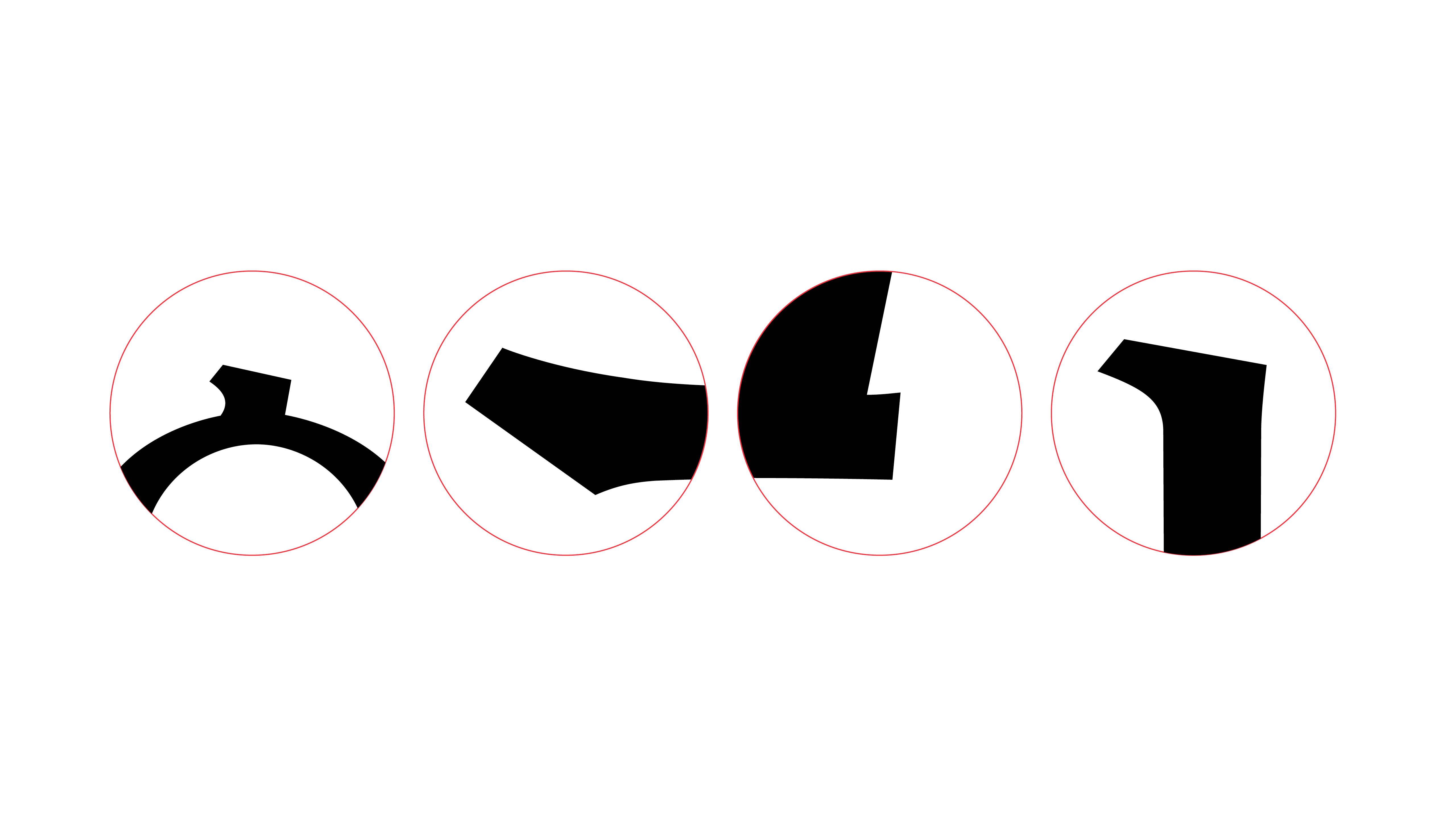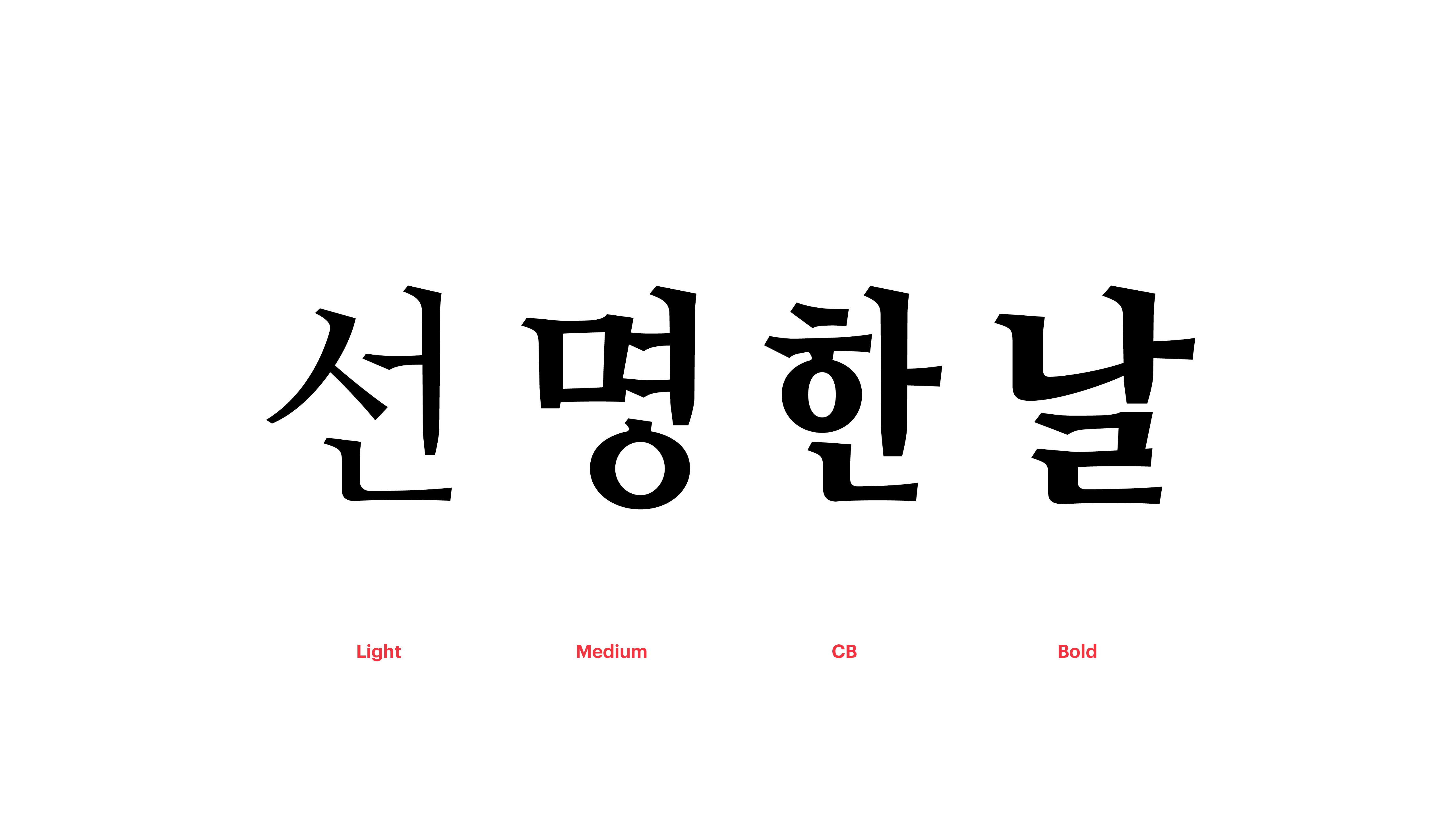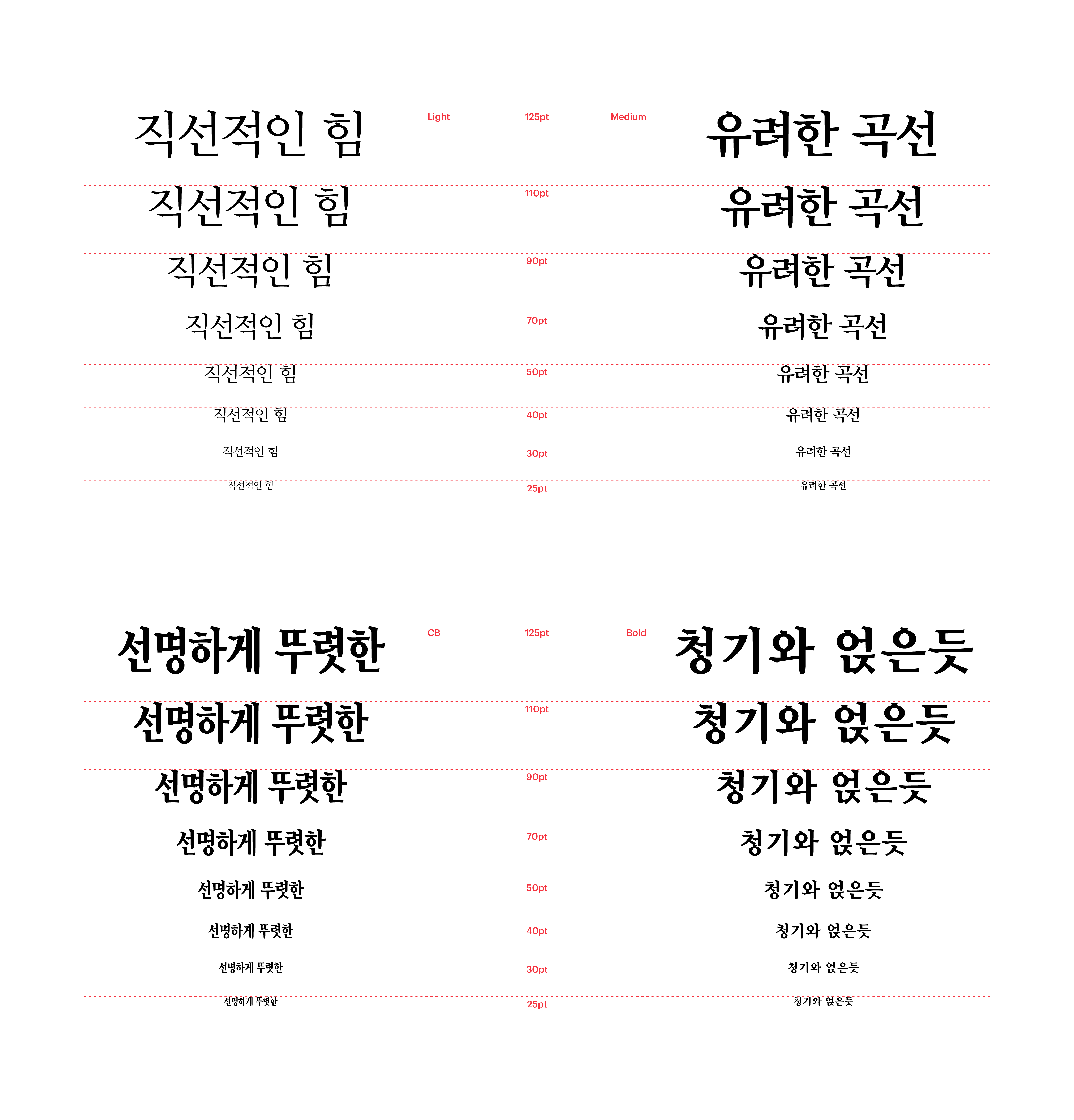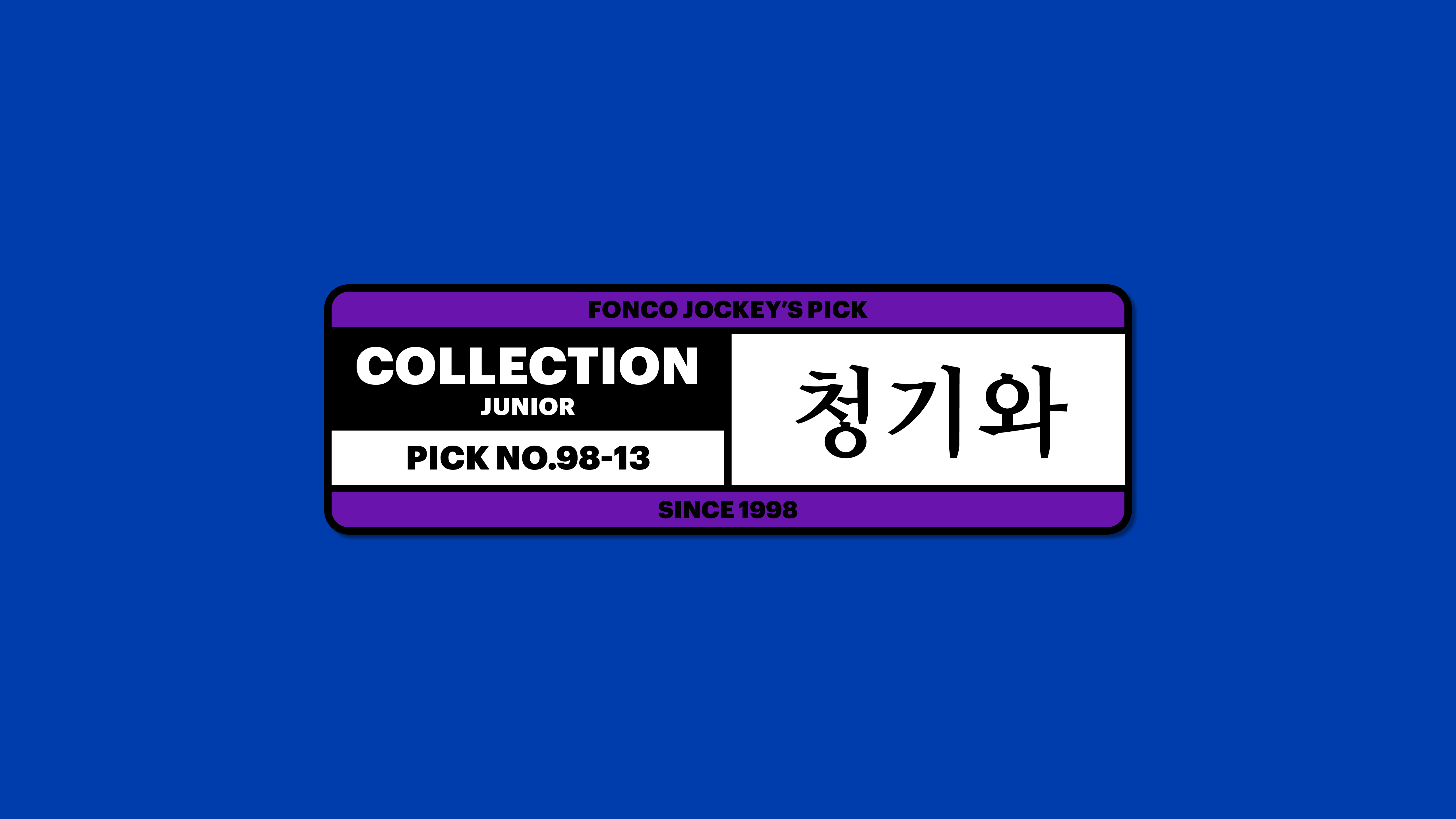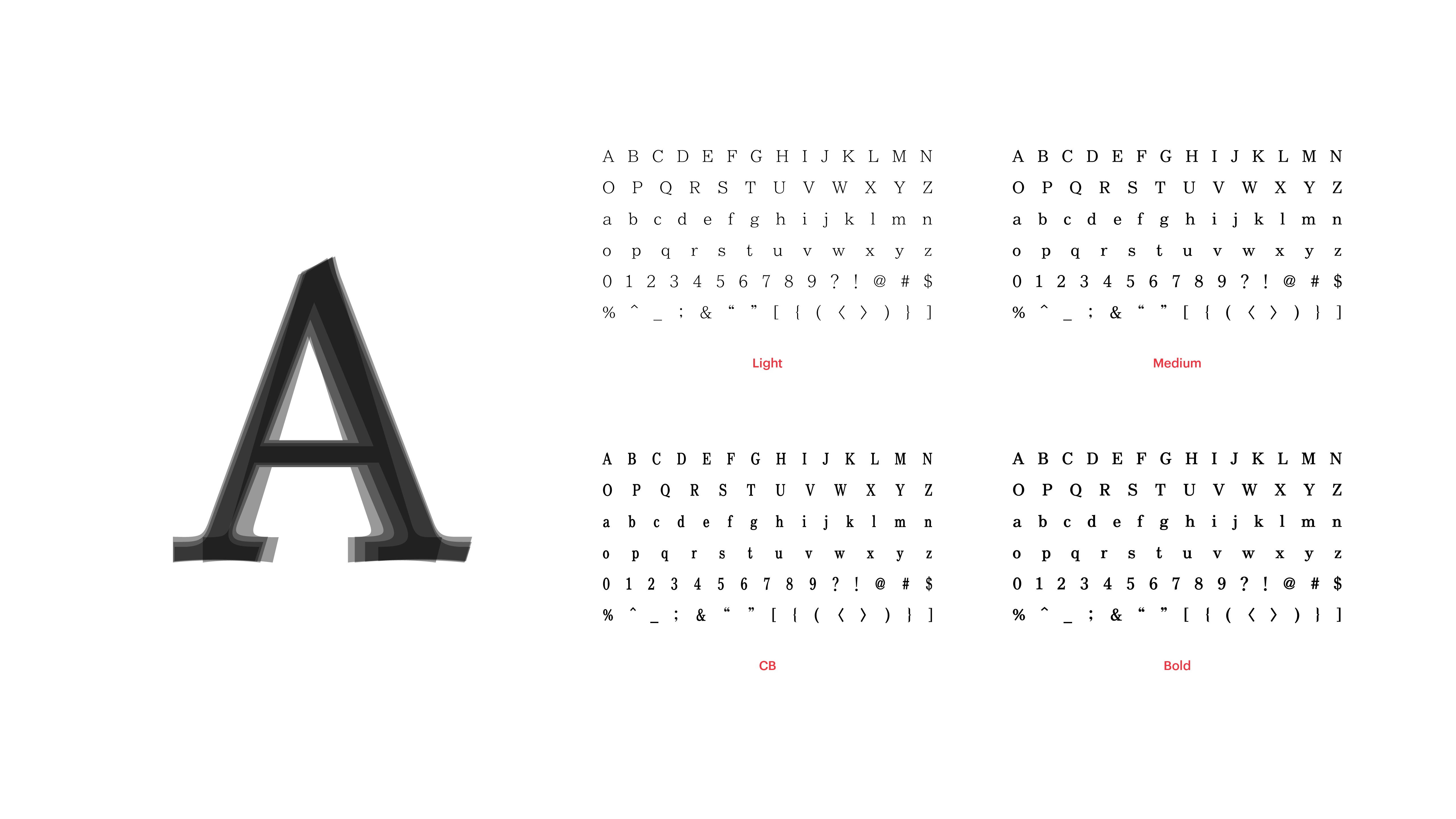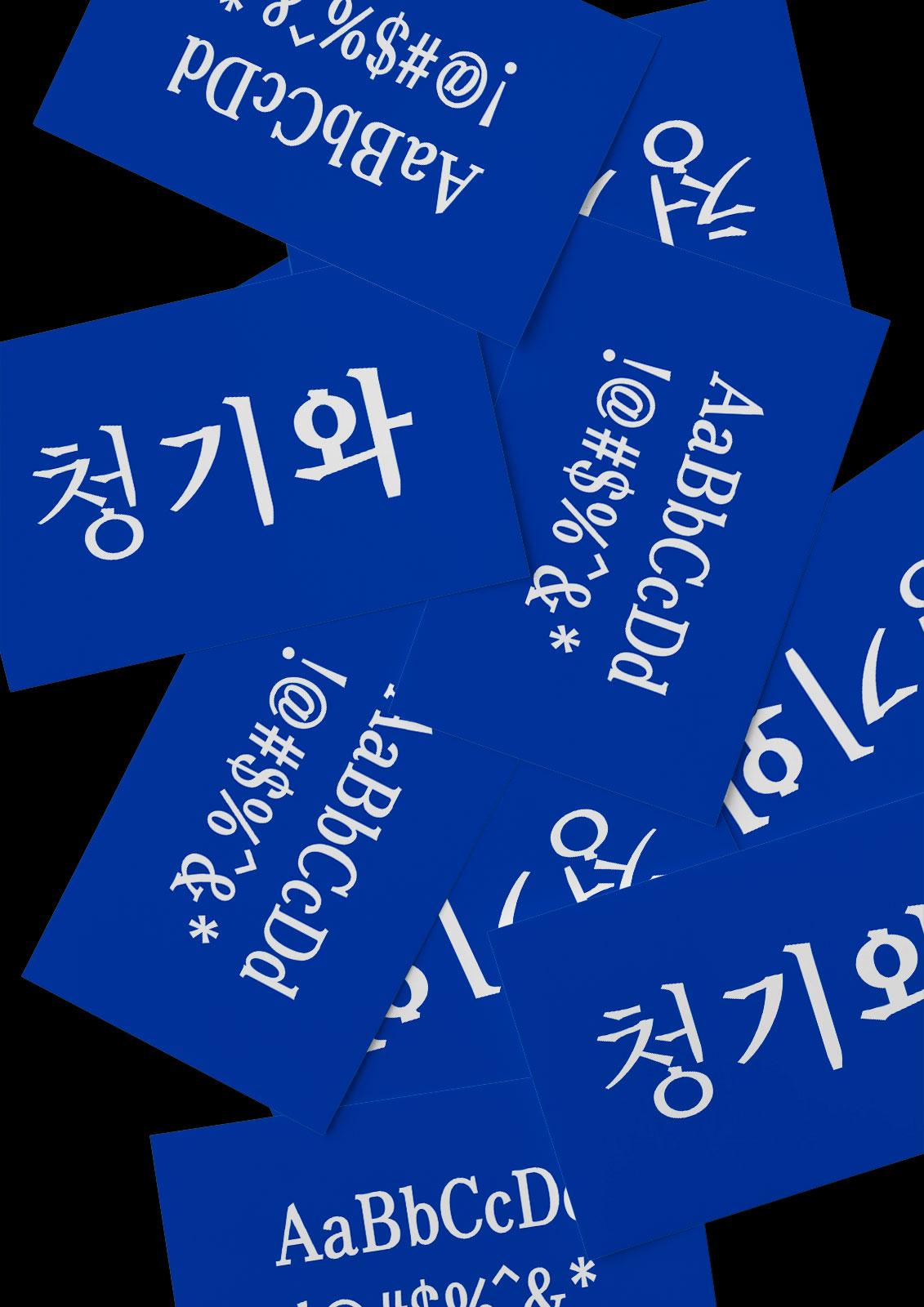
청기와
Yoon 청기와
아이돌 스타와 대배우의 스캔들, 무시무시한 범죄 소식, 원인 모를 이상 기후. 심란한 이야기나 자극적인 사건 사고 대신 내가 지닌 재밌는 이야기를 세상에 널리 알리고 싶다면? 고딕체의 직선적인 힘에 명조체가 지닌 곡선의 유려함을 더해 디자인한 신문 제목용 폰트, 청기와체를 사용해보세요.